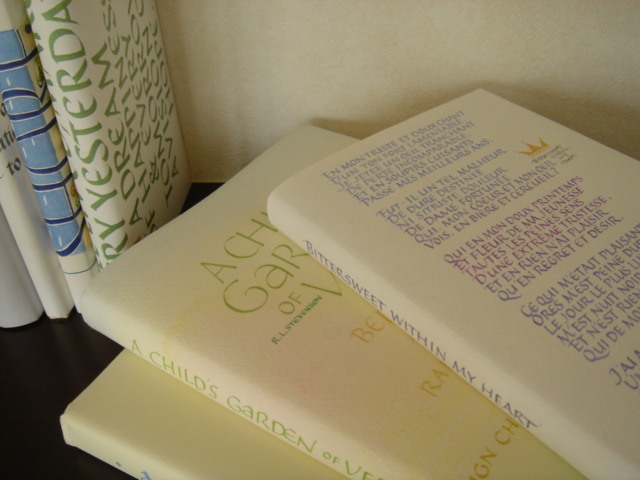
ブックカバー
ところで本にカバーをかけていますか?私は読むとき邪魔なのでカバーをついとってしまいます。棚に並べて置くときもカバー無しのほうが好き。(でもカバーがあるほうが書名が探しやすいのですよねー)
カバー敬遠派の私ですがこんなふうに文字や色で遊んだカバーをつくるのは好きです。書棚の飾りにもなりますよね。写真は気に入りの詩の本のために書いてみたものです。背のタイトルを書くだけならとってもカンタンです。
とってもステキですね。
きっと本も喜んでいるのでは...